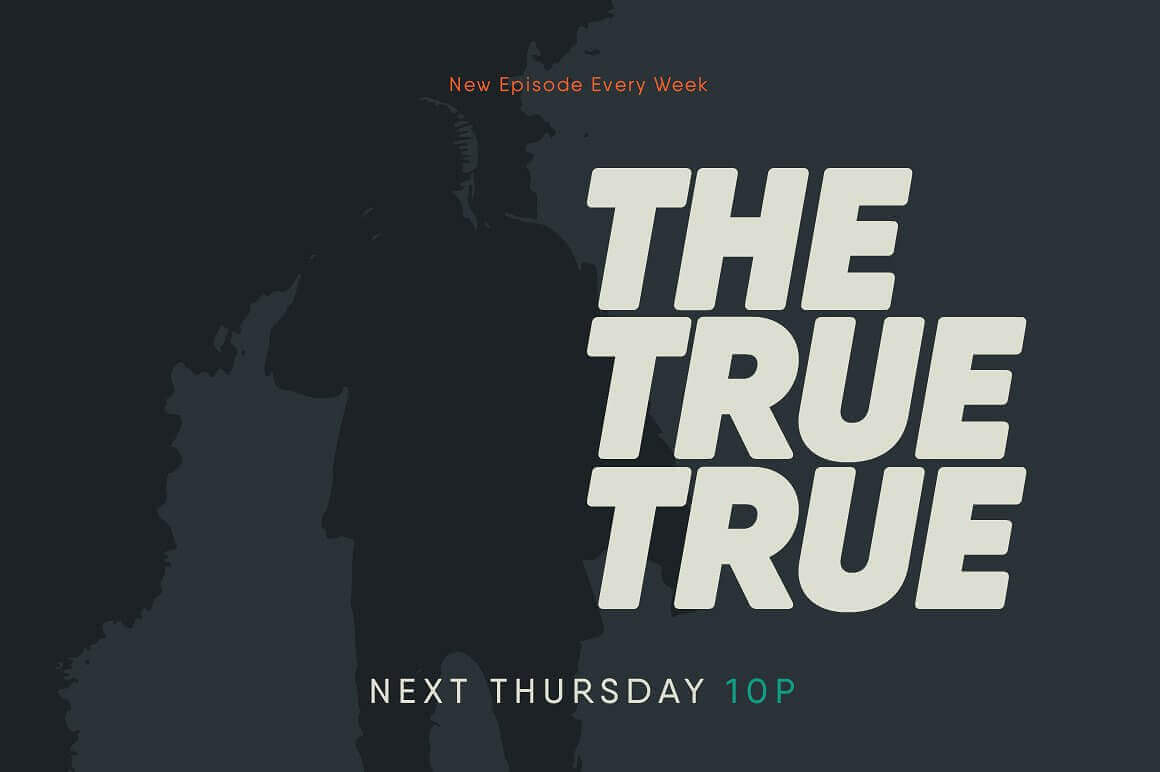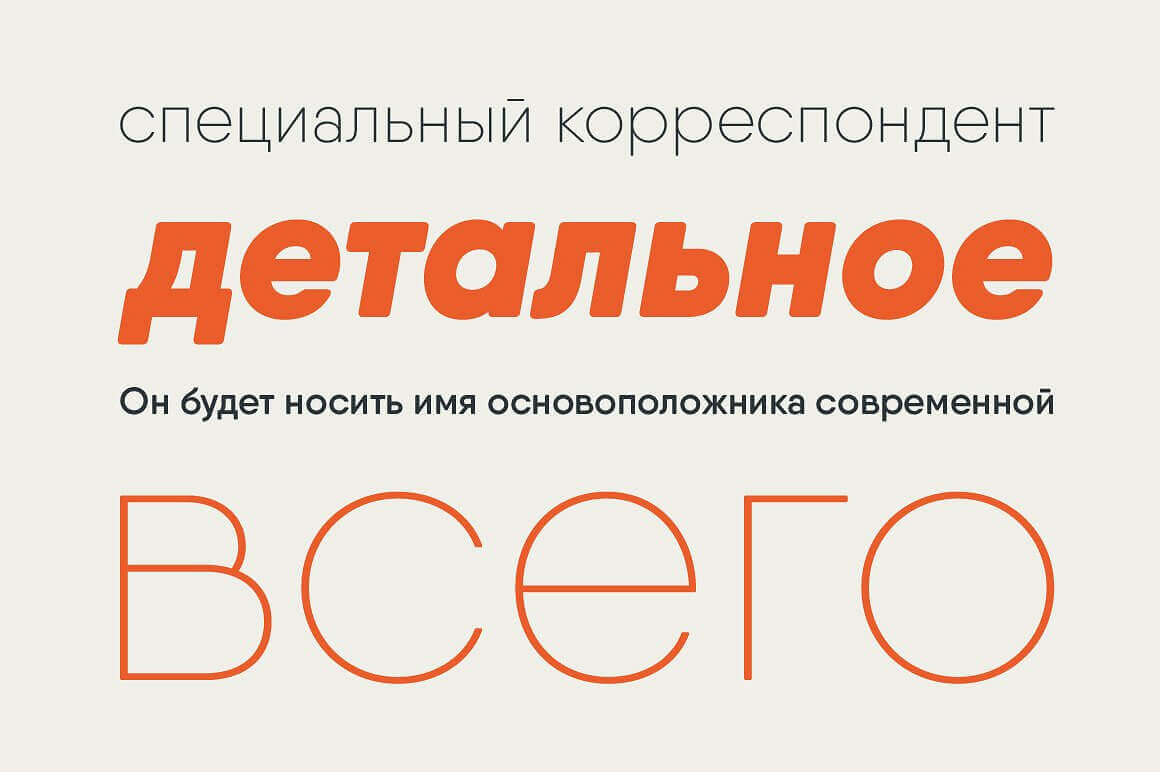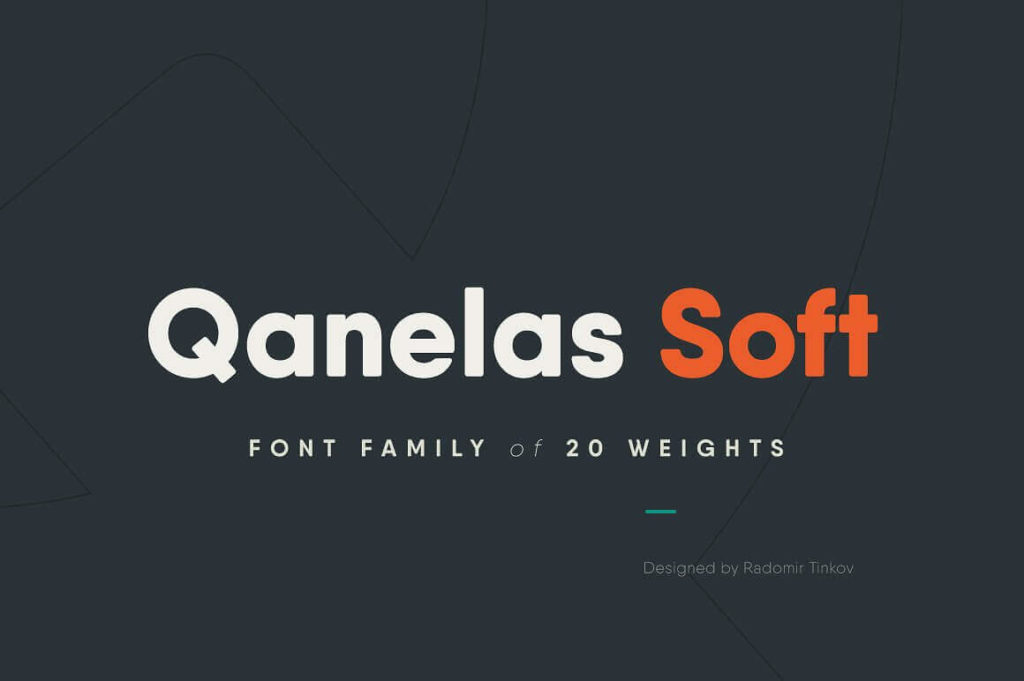
Шрифт Qanelas Soft
это современный гуманистический гротеск с геометрическими элементами, созданный дизайнером Радомиром Тинковым (Radomir Tinkov). Являясь более дружелюбной и мягкой версией оригинальной семьи Qanelas, он отличается округлыми формами и высокой читаемостью. Шрифт полностью адаптирован для кириллического набора, сохраняя при этом естественность и теплоту начертания. Он идеально подходит как для крупных заголовков, так и для основного текста в веб-дизайне и печатной продукции. Вы можете **скачать бесплатно** демо-версию шрифта для ознакомления или приобрести полную лицензию на сайте автора